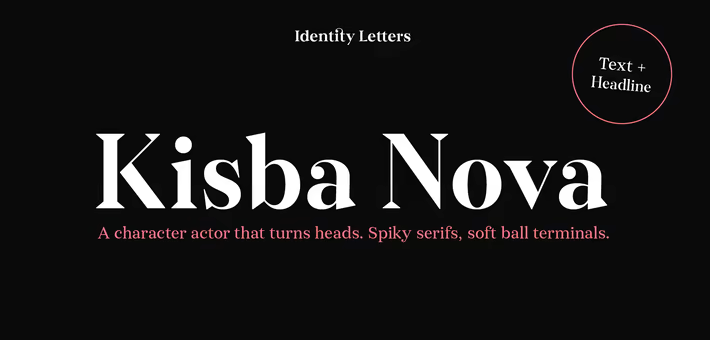
Kisba Nova
- характерный актер, который крутит головой. Колючие засечки, мягкие шарообразные клеммы.
Все внимание на Kisba Nova: введите шрифт, созданный для того, чтобы привлекать внимание. Kisba Nova - это тот самый гость, который присоединяется к вечеринке, и по толпе проходит ропот. Kisba Nova - это чистая харизма.
Противоположности притягиваются: Kisba Nova сочетает острые клиновидные засечки и шипообразные отростки с круглыми и мягкими шаровидными терминалами. Добавьте к этому неоклассический контраст штрихов, и вы получите захватывающий шрифт, движимый визуальными крайностями.
Конечно, Kisba Nova - это дива. Но, в конце концов, это профессионал. Именно поэтому он выпускается в двух оптических размерах: Headline и Text. Это гарантирует, что он будет выглядеть великолепно в любой ситуации.
Подсемейство Kisba Nova Headline отличается фирменным ярким внешним видом и экстравагантными буквами, такими как f и k. Они привносят все волнение шоу-бизнеса в большие приложения - используйте их для размеров 24 пт. и более. Необычайно тонкие и однолинейные диакритические знаки, знаки препинания и символы Kisba Nova Headline дополняют этот современный и элегантный характер.
Kisba Nova Headline состоит из семи начертаний от тонкого до черного, предлагая множество возможностей для создания заголовков и названий. В каждом наборе около 600 символов, что делает его достаточно функциональным для требований опытного типографа. Функции OpenType, такие как большой набор лигатур, расширенная поддержка языков, формы с учетом регистра, различные наборы фигур и стрелок, позволяют создавать сенсационные дизайны как в веб, так и в печатных макетах.
Подсемейство Kisba Nova Text отличается пониженным контрастом, более щедрыми пропорциями букв и более широкими интервалами. Вместо использования броских тонких и однолинейных диакритических знаков, знаков препинания и символов, Kisba Nova Text стремится к более ровной текстуре на странице. Он сохраняет подлинную, элегантную ДНК Kisba, позволяя вам создавать разборчивые копии размером от 9 до 18 пт. Ничто не будет отвлекать вашего читателя - Kisba Nova Text нацелен на удовольствие.
Kisba Nova Text состоит из семи начертаний от тонкого до черного, предлагая множество возможностей для набора основного текста и подзаголовков. В каждом наборе около 600 символов, что делает его достаточно функциональным для требований опытного типографа. Функции OpenType, такие как большой набор лигатур, расширенная поддержка языков, формы с учетом регистра, различные наборы фигур и стрелок, позволяют создавать сенсационные дизайны как в веб, так и в печатных макетах.
Kisba Nova - это двойная природа мягкости и резкости в одном шрифте. Это характерный актер, который кружит голову.